Bạn đang tìm kiếm những font chữ viết tay Việt hóa đẹp và độc đáo cho các dự án thiết kế, in ấn hay sử dụng trên website? Bộ sưu tập font viết tay Việt hóa dưới đây sẽ giúp bạn tạo điểm nhấn sáng tạo cho tiêu đề, thiết kế poster, quảng cáo cũng như các sản phẩm đồ họa khác. Những font này không chỉ hỗ trợ đầy đủ ký tự tiếng Việt mà còn mang phong cách viết tay tự nhiên, phù hợp cho nhiều mục đích sử dụng như thiết kế, in ấn, Photoshop hay các dự án web. Cùng khám phá ngay top những font viết tay Việt hóa đẹp, miễn phí chất lượng cao trong năm 2024 nhé!
Bộ sưu tập font viết tay Việt hóa đang trở thành một nguồn cảm hứng bất tận cho các designer. Với hơn 1000 mẫu font chữ, bạn sẽ tìm thấy từ chữ ký tinh tế đến những nét viết tay đầy nghệ thuật, tất cả đều tích hợp đầy đủ ký tự tiếng Việt, bao gồm cả dấu thanh, giúp cho mọi thiết kế trở nên thân thiện và gần gũi hơn.
Chúng tôi hướng đến sự chất lượng thay vì số lượng, nên kho font việt hóa DFVN không chỉ phong phú về chủng loại mà còn tỉ mỉ trong từng chi tiết. Những phông chữ viết tay được thiết kế để phù hợp với cả tiêu đề lẫn nội dung ngắn, mang đến một cảm nhận tự nhiên như chính bản thân bạn đang viết.
Một vài font nổi bật như Amber Queen Signature hay Buffalo Handwritten chắc chắn sẽ khiến cho những dự án của bạn được tỏa sáng hơn bao giờ hết. Bạn có thể dễ dàng tìm thấy những font tuyệt đẹp này trên Canva để chuẩn bị cho những dịp đặc biệt sắp tới như lễ 30.4. Hãy khám phá ngay để làm mới những thiết kế của mình!
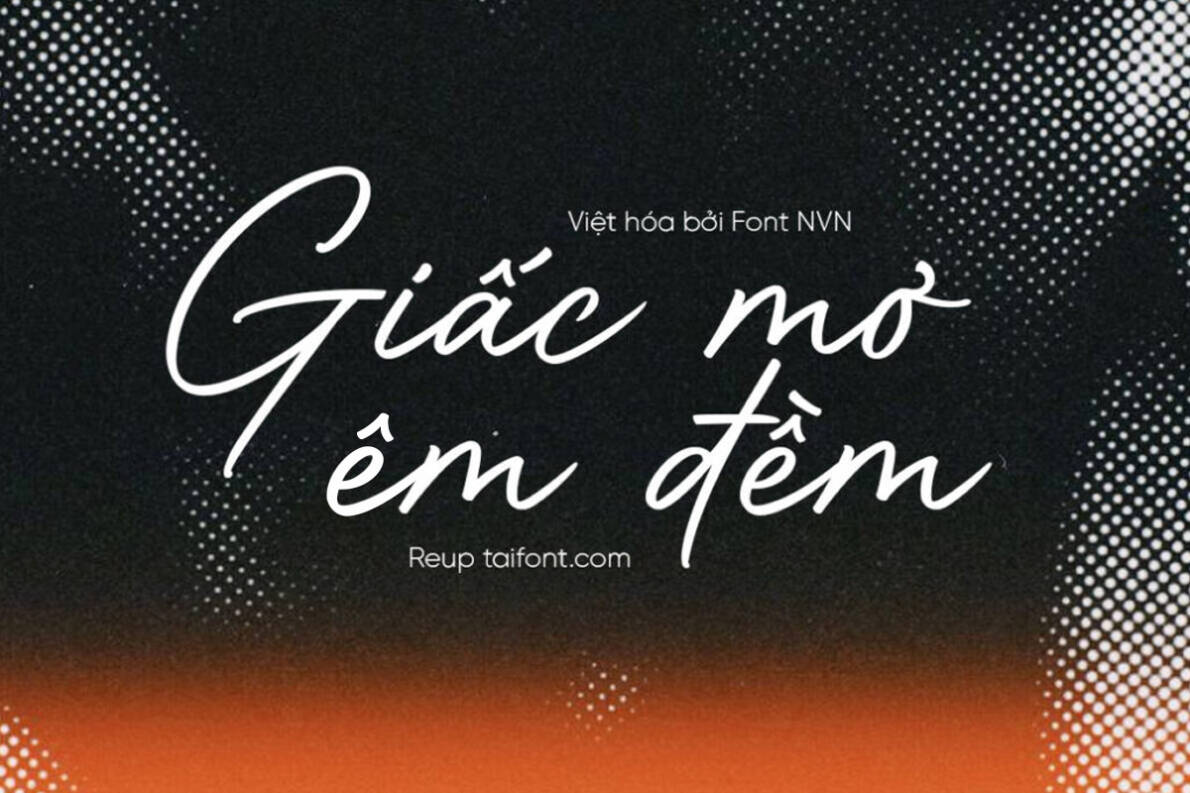
Trong thế giới thiết kế ngày nay, việc sử dụng font chữ viết tay Việt hóa không chỉ giúp mang lại nét độc đáo mà còn thể hiện cá tính riêng. Bộ sưu tập hơn 1000 font chữ việt hóa chữ ký, viết tay, với những mẫu tiêu biểu như SVN-Antique, iCiel Romantic, hay UTM Snow, đã đáp ứng nhu cầu đa dạng từ người thiết kế. Chúng không chỉ đẹp mắt mà còn hoàn thiện với đầy đủ các ký tự tiếng Việt.
Font chữ viết tay Việt hóa được thiết kế mô phỏng nét chữ tự nhiên, mang lại cảm giác gần gũi và thân thuộc. DFVN chú trọng vào chất lượng, mỗi font đều được kiểm tra kỹ lưỡng và có thể sử dụng cho cả tiêu đề lẫn nội dung ngắn. Đặc biệt, những mẫu này còn hỗ trợ biến thể variable, đem đến sự linh hoạt cho các dự án thiết kế.
Nếu bạn đang tìm kiếm những font đẹp cho việc edit ảnh hoặc vlog, đặc biệt là cho dịp 30.4 sắp tới, hãy khám phá ngay bộ sưu tập font viết tay Vintage hay FC Gastie. Chắc chắn rằng, những nét chữ này sẽ tạo điểm nhấn cho tác phẩm của bạn, khiến chúng trở nên nổi bật và cuốn hút hơn.
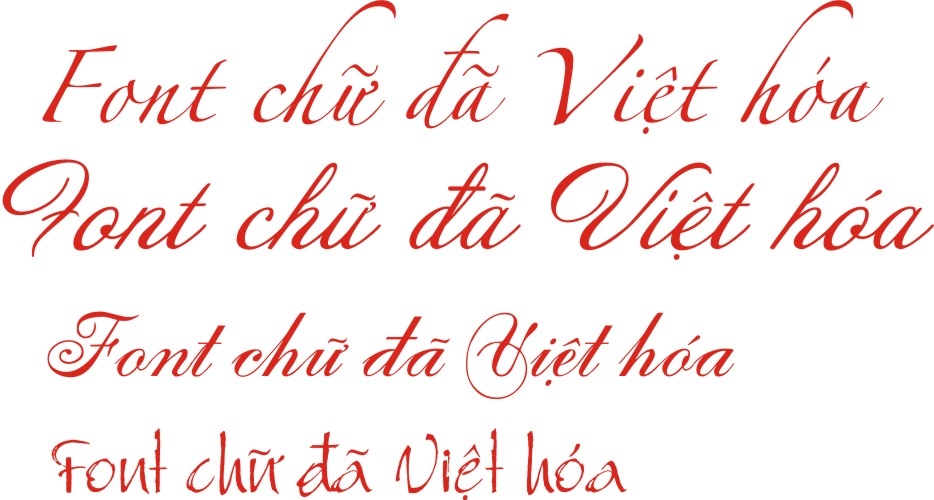
Font chữ viết tay đẹp đang trở thành một xu hướng hot trong thiết kế, đặc biệt là cho logo và các sản phẩm sáng tạo. Những font này không chỉ mô phỏng nét chữ viết tay mà còn được Việt hóa với đầy đủ các ký tự tiếng Việt, bao gồm cả dấu thanh và dấu câu. Với bộ sưu tập 1000+ font chữ Việt hóa, bạn có thể dễ dàng tìm thấy những kiểu chữ như chữ ký, chữ viết tay hay thậm chí là phong cách vintage độc đáo.
Chẳng hạn, các font như Parisienne, Grand Estonia và Sacramento đều mang lại cảm giác nhẹ nhàng, thú vị cho thiết kế của bạn. Hơn nữa, các phông chữ thảo giúp tạo dấu ấn cá nhân cho logo, mang lại sự khác biệt so với các thiết kế thông thường. Một số font nổi bật như Shantell Sans còn được phát triển từ nét viết tay của nghệ sĩ, đem lại cảm xúc và câu chuyện riêng cho mỗi sản phẩm.
Ngoài ra, nhiều font chữ viết tay miễn phí cũng có sẵn, giúp bạn dễ dàng kết hợp phong cách DIY vào thiết kế của mình. Việc sử dụng phông chữ viết tay không chỉ tăng thêm sức hấp dẫn mà còn làm cho thiết kế trở nên gần gũi và ấm áp hơn.
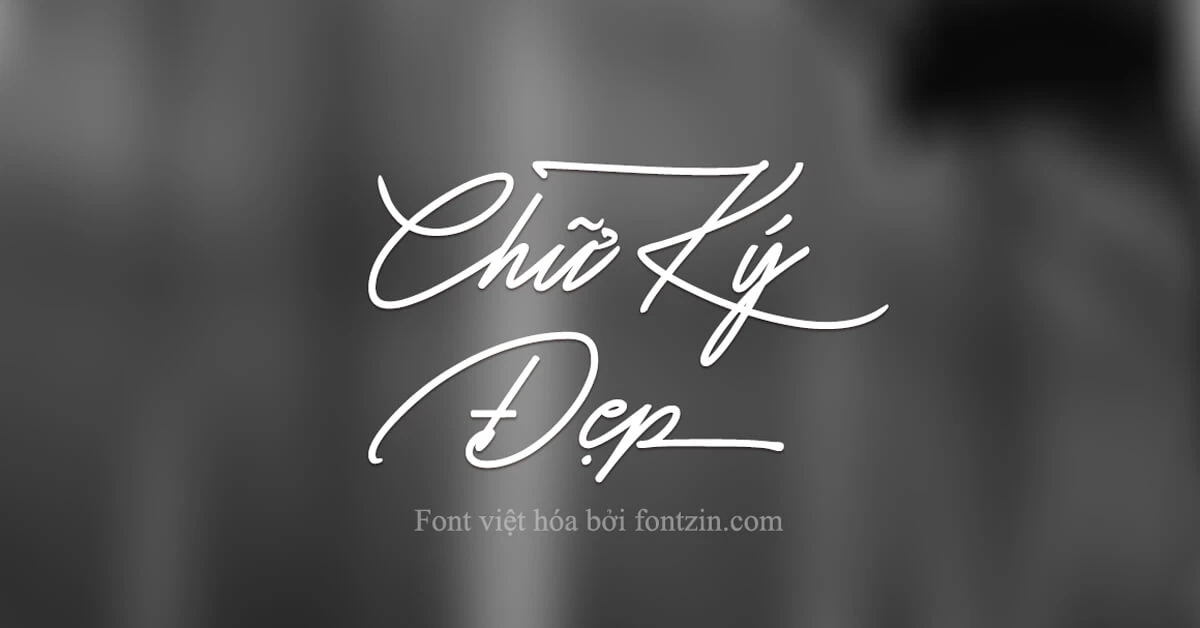
Bộ sưu tập Font viết tay Việt hóa hiện có hơn 100 kiểu chữ hấp dẫn, được thiết kế để mang lại sự lựa chọn phong phú cho nhu cầu sáng tạo của bạn. Với các phong cách đa dạng như brush mạnh mẽ, handwritten tinh tế và calligraphy mềm mại, bạn có thể dễ dàng tìm thấy font chữ phù hợp với từng dự án thiết kế.
Các font chữ viết tay này không chỉ đẹp mà còn được tích hợp đầy đủ các ký tự tiếng Việt, bao gồm cả dấu thanh và dấu câu. Điều này giúp bạn dễ dàng tạo ra những sản phẩm thiết kế mang tính cá nhân hóa và gần gũi. Bộ sưu tập này không chỉ dành cho những ai làm thương hiệu hay thiết kế đồ họa mà còn phục vụ cho các bạn yêu thích viết chữ đẹp.
Ngoài ra, những font miễn phí như DFVN Soyuz Grotesk hay TH Milyah hứa hẹn sẽ mang lại sự mới mẻ cho các tác phẩm của bạn. Hãy ghé thăm website FontVietHoa.VN để tải ngay những bộ font tuyệt đẹp, dễ dàng cài đặt và sử dụng cho các dự án sáng tạo của mình nhé!
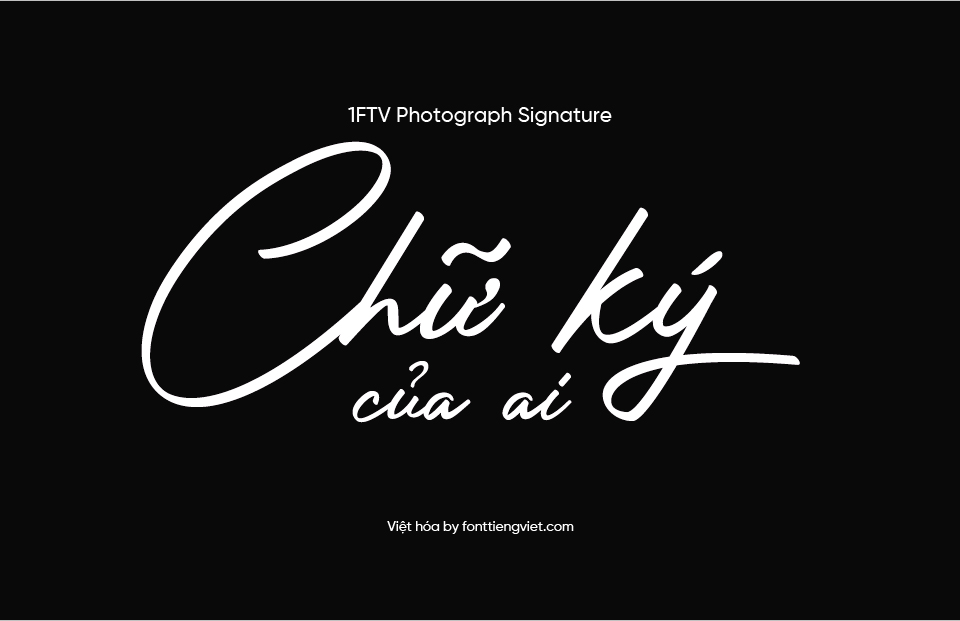
Nếu bạn đang tìm kiếm những font viết tay đẹp cho thiết kế, d3design.vn đã chọn ra 10 font chữ đặc biệt hoàn toàn miễn phí để bạn tham khảo. Những font này không chỉ mang đến sự sáng tạo mà còn tạo nên một phong cách độc đáo cho các dự án của bạn. Điều thú vị là chúng thường mang những đường nét mềm mại, chi tiết hình học độc đáo và sự kết hợp hài hòa giữa chữ in hoa và chữ thường.
Trong số đó, có những cái tên nổi bật như Dancing Script, UTM Thư Pháp Thiên Ân và Loveya Script. Chúng đều phù hợp cho nhiều loại thiết kế khác nhau, từ tiêu đề đến nội dung ngắn. Với hơn 1000 font Việt hóa chữ ký và viết tay, bạn sẽ dễ dàng tìm ra lựa chọn phù hợp cho các ý tưởng sáng tạo của mình.
Ngoài ra, font chữ Variane Script với phong cách điển, nét tròn nhẹ nhàng cũng nhận được nhiều yêu thích trong giới designer. Các font này không chỉ mang lại vẻ đẹp mà còn rất tiện lợi, vì bạn có thể tải về dễ dàng và sử dụng cho cả dự án thương mại. Hãy khám phá kho font Việt hóa đa dạng này và biến tấu thiết kế của bạn trở nên ấn tượng hơn!
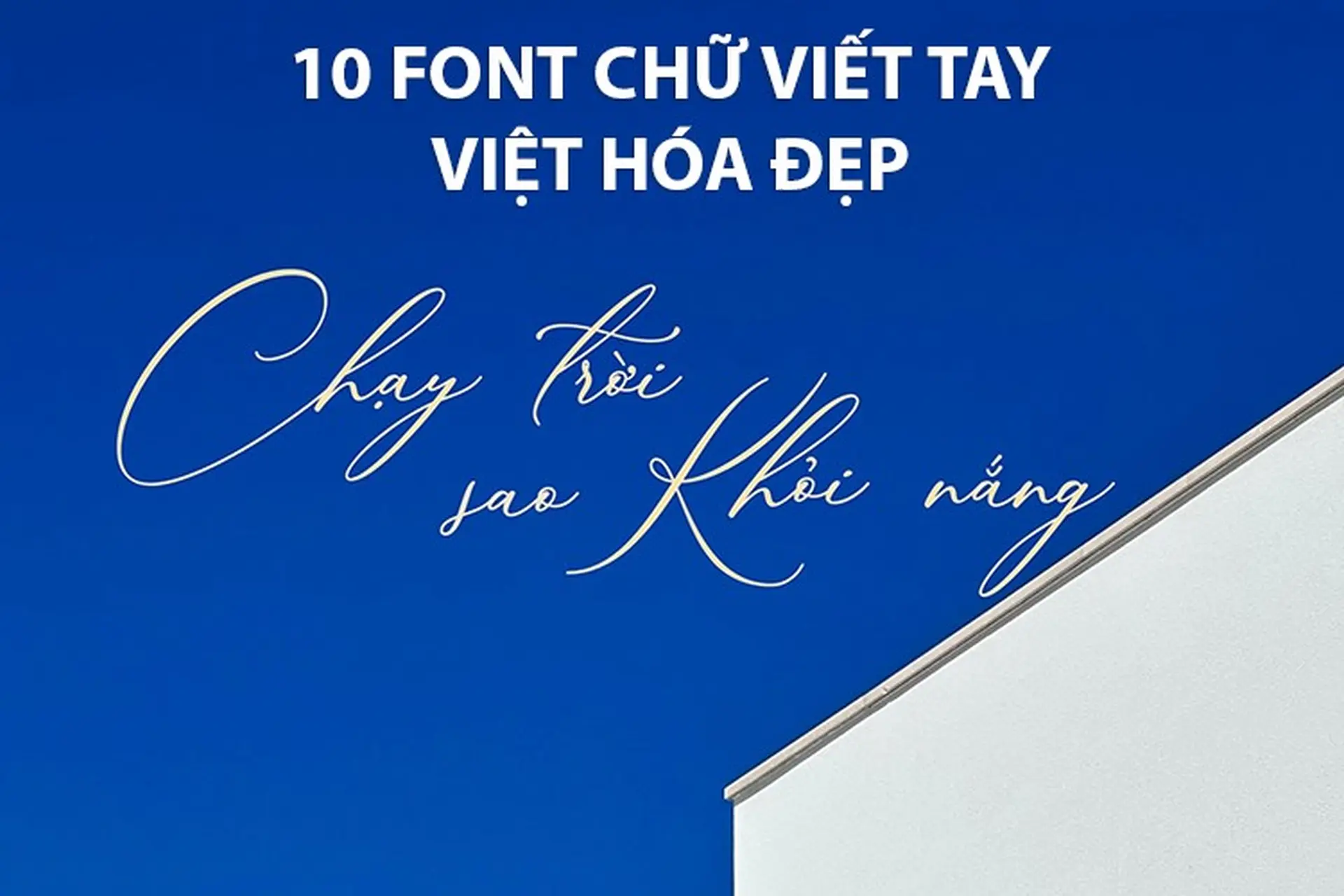
Font viết tay đẹp, đặc biệt là các font chữ Script, đang trở thành xu hướng trong thiết kế poster và banner hiện nay. Với cấu trúc thanh mảnh và những đường cong mềm mại, các font này không chỉ mang lại vẻ đẹp tinh tế mà còn tạo cảm giác gần gũi, ấm áp cho người nhìn. Chúng rất lý tưởng cho các dự án như poster phim, bìa sách hay các sản phẩm sáng tạo khác.
Trong danh sách những font chữ viết tay nổi bật, không thể không nhắc đến Dancing Script, UTM Thư Pháp Thiên Ân và Loveya Script. Mỗi loại font đều có những đặc điểm riêng, từ sự mềm mại của TH Flarida cho đến nét hiện đại của TT Firs Neue. Những font này không chỉ dễ dàng sử dụng mà còn giúp bạn tạo điểm nhấn cho thiết kế của mình.
Bạn có thể dễ dàng tạo ra những mẫu poster độc đáo bằng các công cụ thiết kế như Canva. Đặc biệt, với bộ sưu tập hơn 15 font chữ viết tay Việt hóa đẹp mắt, bạn sẽ có nhiều lựa chọn phong phú để làm cho dự án của mình thật sự nổi bật và ấn tượng.
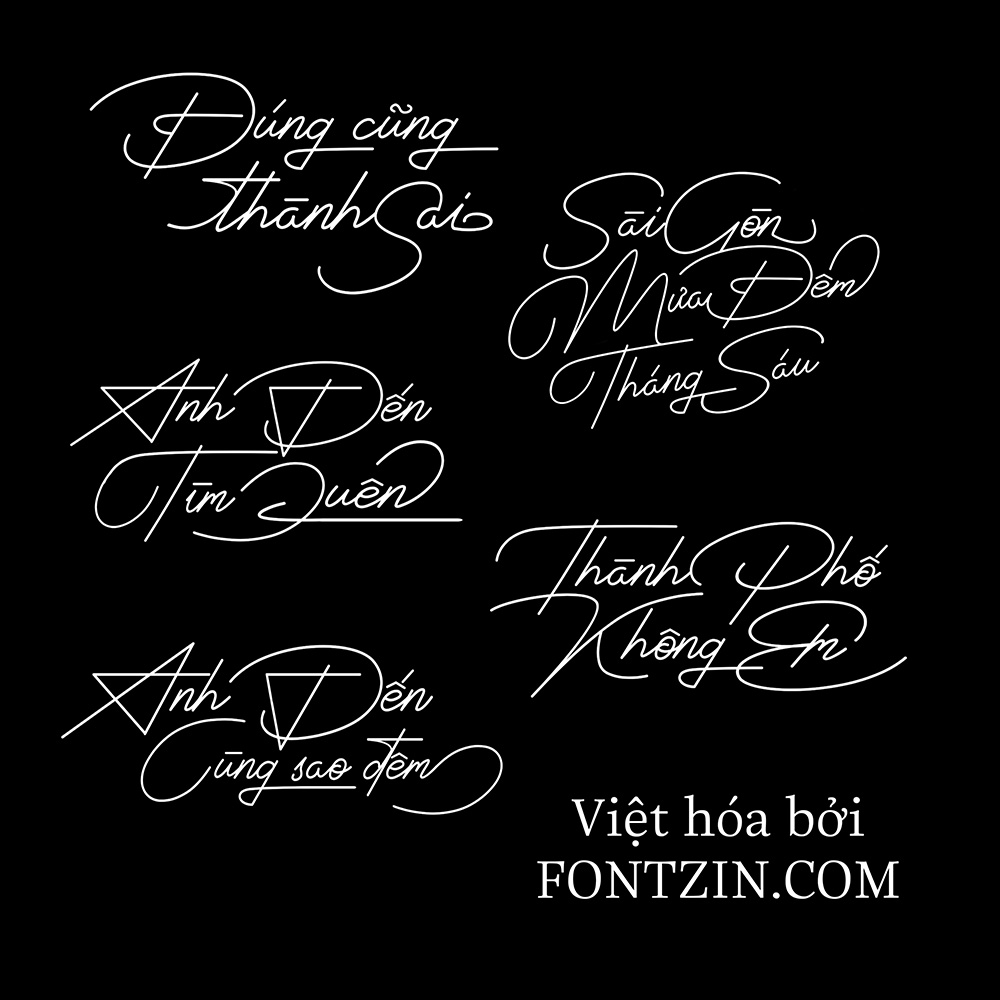
Nếu bạn là người yêu thích thiết kế, thì bộ sưu tập hơn 1000 font viết tay Việt hóa chắc chắn sẽ là nguồn tài nguyên quý giá cho bạn. Những font chữ này được thiết kế để mô phỏng nét đẹp của chữ viết tay, vừa mang đến sự mềm mại lại vừa độc đáo, giúp bài thiết kế của bạn nổi bật hơn.
Trong số đó, có những tên tuổi đình đám như Dancing Script, UTM Thư Pháp Thiên Ân hay Loveya Script. Những font này không chỉ hỗ trợ đầy đủ các ký tự tiếng Việt mà còn rất thích hợp cho tiêu đề, poster hay bất kỳ dự án sáng tạo nào của bạn.
Ngoài ra, chúng tôi còn tổng hợp 10 font chữ viết tay Việt hóa được yêu thích nhất trong năm 2023, như Amber Queen Signature hay Just Awesome, giúp cho bạn có thêm nhiều lựa chọn phong phú. Sử dụng chúng, bạn sẽ có thể tạo ra những chữ ký nghệ thuật hay chèn text vào ảnh một cách hoàn hảo. Hãy trải nghiệm và cảm nhận sự khác biệt từ những font chữ Việt hóa tuyệt đẹp này nhé!
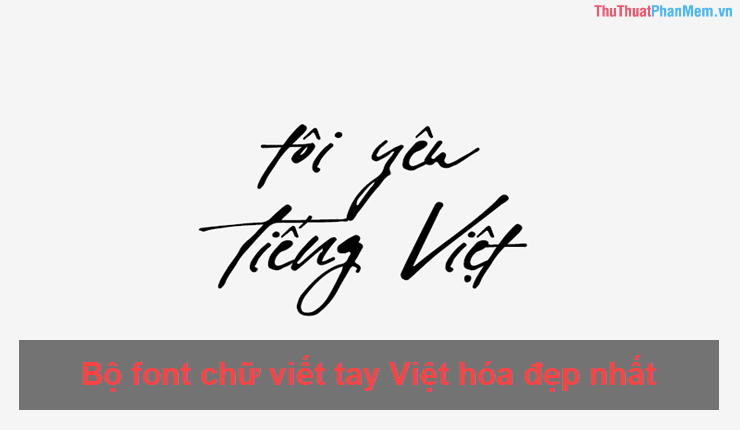
Font viết tay Việt hóa hiện đang được ưa chuộng trong thiết kế quảng cáo nhờ vào vẻ đẹp và sự độc đáo mà chúng mang lại. Chẳng hạn như font 1FTV VIP Normiyola, một kiểu chữ cổ điển, mạnh mẽ rất phù hợp cho những dự án lịch sử hoặc in ấn ấn phẩm quảng cáo. Đặc biệt, nó được Việt hóa hoàn chỉnh với đầy đủ các ký tự tiếng Việt, từ dấu thanh cho đến dấu câu, tạo điều kiện thuận lợi cho việc sử dụng trong các ngữ cảnh khác nhau.
Ngoài ra, bộ sưu tập font chữ viết tay Việt hóa còn bao gồm nhiều lựa chọn thú vị như DFVN Bungalow hay DFVN TAN – CHARLIE, tạo cảm giác vừa hoài cổ lại mới mẻ. Các font chữ này không chỉ đáp ứng nhu cầu thiết kế banner, poster hay logo mà còn giúp tăng thêm phần sáng tạo và thu hút cho các ấn phẩm đồ họa.
Nếu bạn đang tìm kiếm những font chữ viết tay Việt hóa đẹp mắt cho dự án của mình, đừng bỏ qua bộ sưu tập lên tới 1100 mẫu font chữ này. Chúng đều được thiết kế chuyên nghiệp và dễ dàng cài đặt trên các phần mềm thiết kế như Photoshop, Illustrator hay Word. Hãy trải nghiệm và tìm cho mình một font chữ ưng ý!
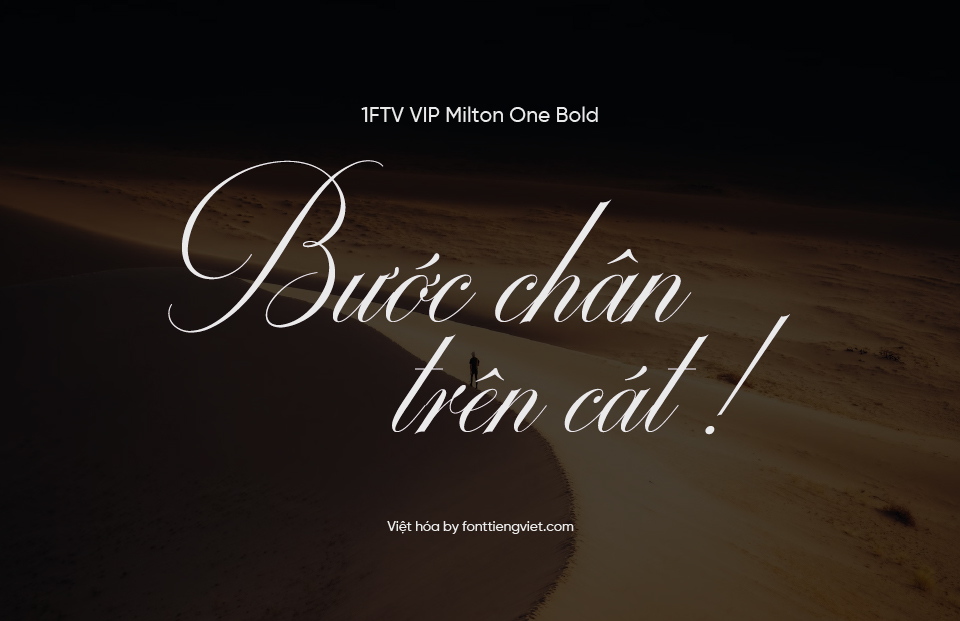
Nếu bạn là một nhà thiết kế và đang tìm kiếm những font chữ viết tay đẹp và ấn tượng cho các dự án của mình, bộ sưu tập hơn 1000 font việt hóa chứ ký chắc chắn sẽ làm bạn hài lòng. Trong đó, có rất nhiều font chữ viết tay hoàn hảo cho thiết kế đồ họa, poster quảng cáo hay thiệp chúc mừng. Một số font nổi bật như Classique Saigon, L’Hanoienne, hay Alek đang rất được ưa chuộng trong năm 2023.
Đặc biệt, bộ font chữ này còn bao gồm những lựa chọn miễn phí, giúp bạn dễ dàng tìm và tải về mà không phải lo lắng về vấn đề chi phí. Ngoài ra, d3design.vn đã quy tụ nhiều mẫu chữ ký đẹp, dễ dàng cho bạn tham khảo và sử dụng.
Để cài đặt các font chữ này vào Photoshop, bạn chỉ cần làm theo hướng dẫn đơn giản từ SaDesign. Quá trình cài đặt không hề phức tạp, giúp bạn nhanh chóng có được font chữ yêu thích trong bộ sưu tập của mình. Hãy thử ngay những font chữ viết tay việt hóa để tạo ra những sản phẩm thiết kế độc đáo và ấn tượng nhé!
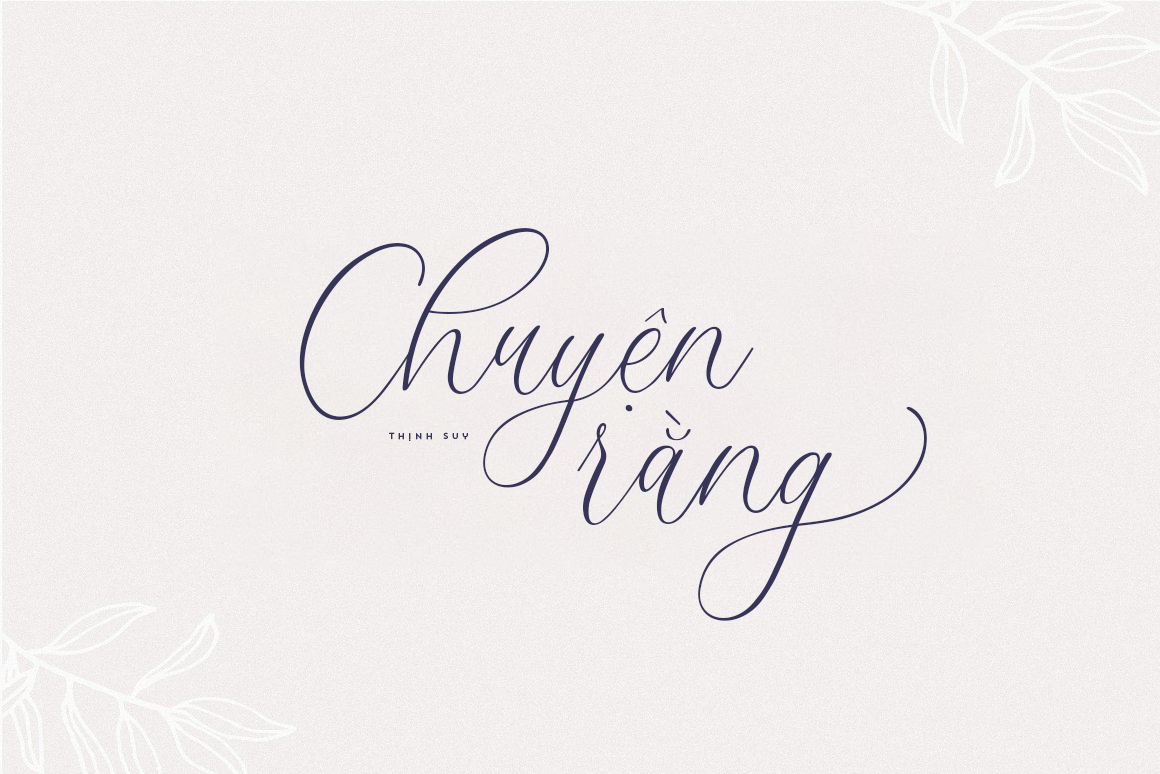
Nếu bạn đang tìm kiếm những font chữ viết tay đẹp và đã được Việt hóa cho thiết kế, bộ sưu tập 1000+ font của chúng tôi chắc chắn sẽ làm bạn hài lòng. Chúng tôi đã sưu tầm hơn 1100 kiểu chữ, bao gồm các phông chữ mang phong cách brush mạnh mẽ, handwritten tinh tế và calligraphy mềm mại, phù hợp với nhu cầu sáng tạo của mọi người.
Mỗi font chữ viết tay Việt hóa đều mô phỏng nét chữ tự nhiên, giúp bạn dễ dàng thể hiện cảm xúc trong các thiết kế. Đặc biệt, các ký tự tiếng Việt, bao gồm dấu thanh và dấu câu, được tích hợp hoàn hảo. Bạn không nên bỏ qua những font cực đẹp trên Canva như Dancing Script, UTM Thư Pháp Thiên Ân, hay Loveya Script, cho những dịp đặc biệt sắp tới.
Kho font Việt hóa DFVN không chỉ chú trọng đến chất lượng mà còn đảm bảo tính đa dạng, từ những font tiêu đề đến nội dung ngắn. Chúng tôi tự hào mang đến những sản phẩm được biên tập tỉ mỉ, giúp bạn dễ dàng lựa chọn cho các dự án thiết kế của mình. Hãy lưu lại để sử dụng cho các bức ảnh hay vlog của bạn nhé!
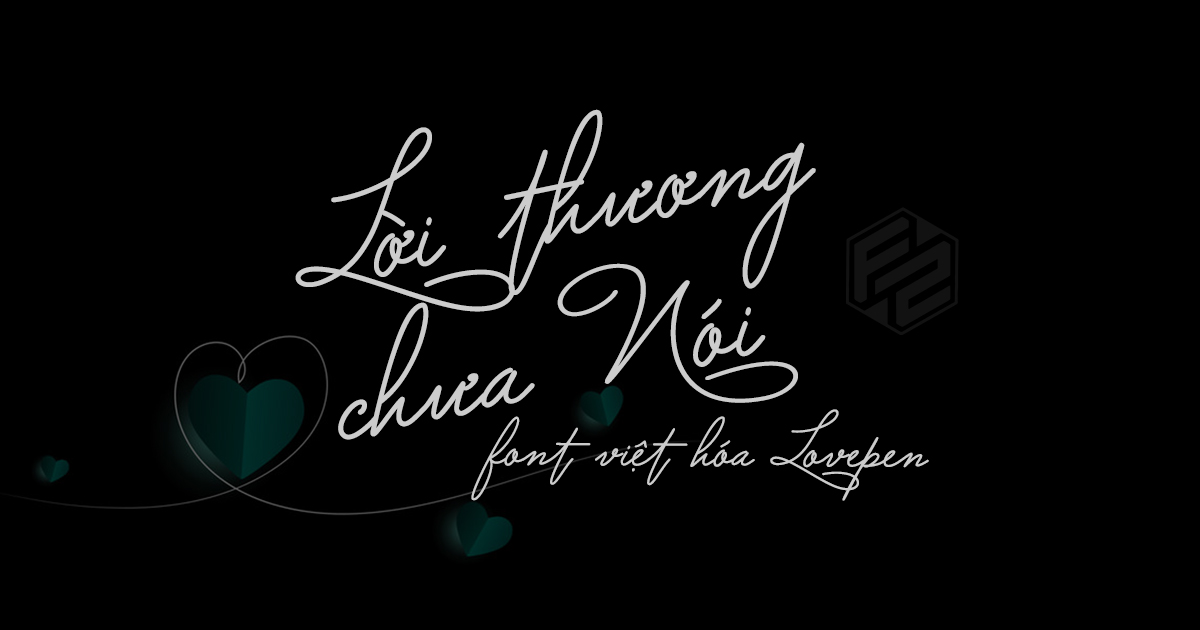
Kết bài cho bài viết:
Tóm lại, việc phát triển kỹ năng cá nhân là một quá trình liên tục và cần sự kiên trì. Những nỗ lực trong việc nâng cao bản thân không chỉ mang lại lợi ích cá nhân mà còn góp phần tích cực vào sự phát triển chung của xã hội. Chúng ta hãy luôn học hỏi, mở rộng kiến thức và rèn luyện bản thân mỗi ngày để trở thành phiên bản tốt hơn của chính mình. Hy vọng rằng mỗi người sẽ tìm thấy động lực và hướng đi đúng đắn trong hành trình phát triển này, từ đó tạo ra những bước tiến vững chắc và ý nghĩa trong cuộc sống.